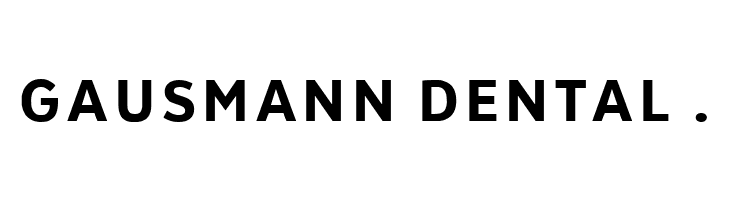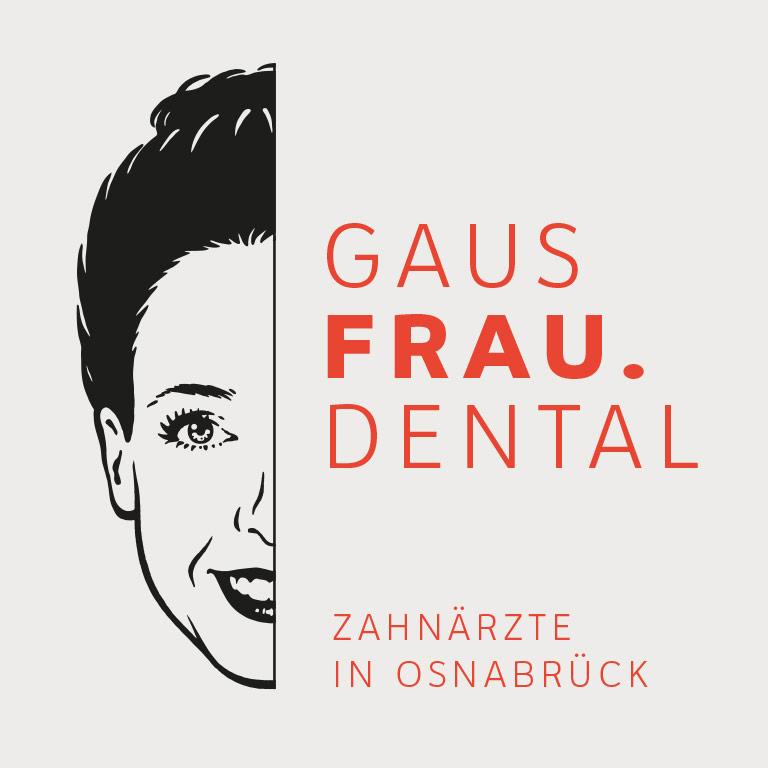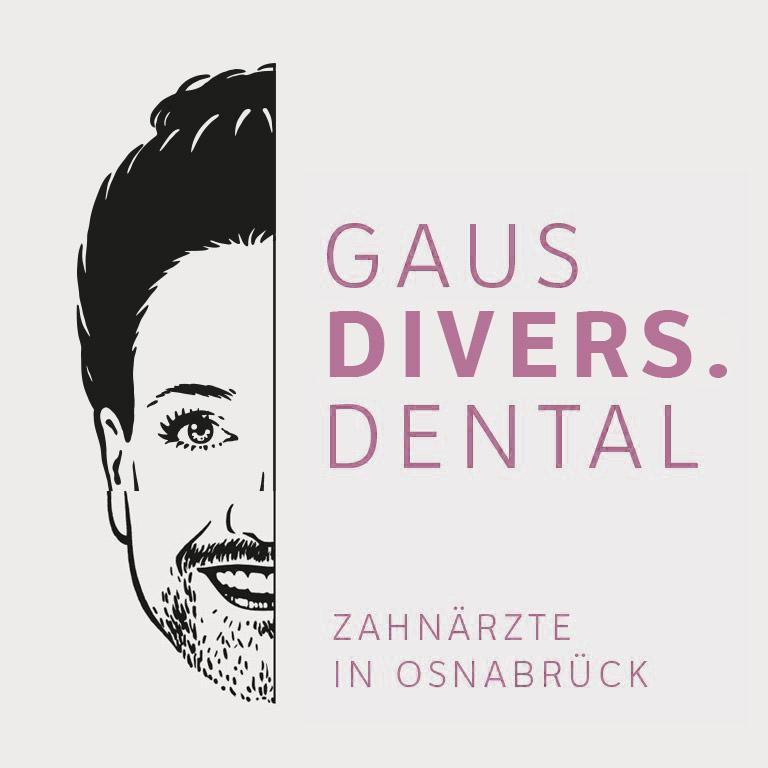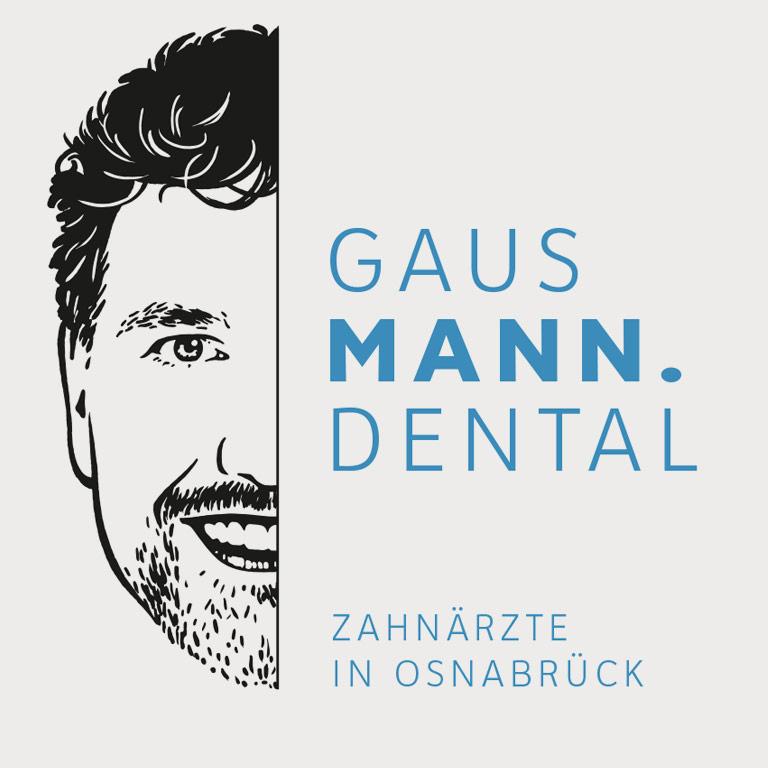
Suche Schriftart von Logo einer Zahnarztpraxis in Osnabrück (2019)
ich suche die Schriftart (oder sehr ähnlich), die in dem Logo der Praxis Gausmann aus Osnabrück verwendet wurde. Das Logo ist in diesem Jahr entstanden. Wenn möglich sollte die Schrift bitte kostenlos verfügbar sein. Ich benötige die Schrift für ein persönliches Geschenk zur Neueröffnung.
Das CD ist heutzutage im Zeitalter des Gendermainstreams extrem unangemessen.
Stimmt, eines fehlt ja noch:
Du meinst beim fotznspangler? Das sind Einzelbuchstaben, die auf die Schindeln aufgebracht wurden. Holz lebt, daher gibt’s auch keine Grundlinie mehr.
...seine Frau hat eine Praxis die heißt Gausfrau 😉
Nein, in ZAHNARZT.